Alapjai tipográfia
Tipográfia - az egyik legfontosabb szempont a web design, mert ennek segítségével a fő információt továbbítják. Sajnos, sok a tervezők és a vásárlók félnek merész kísérlet választja projektjeik számára egy vagy két „megbízható” font.
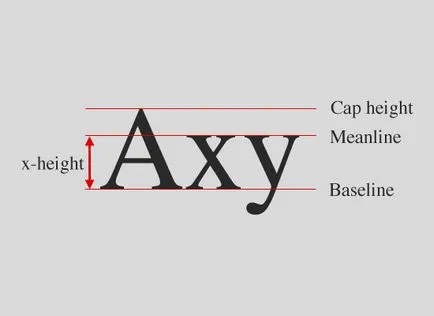
Headset ellen betűtípusok - mi a különbség?
Sokan használják a „Headset” és a „font” szinonimaként. Valójában ez nem ugyanaz a dolog, most fogom magyarázni, hogy miért.
Headset - stílusában hasonló sor karakterek írhatók / print. Ez a számok, betűk, szimbólumok. Betűtípus - szűkebb fogalom kotroe több tényező határozza meg, például méret, és a stílus. Általában Arial - ez a fejhallgató és Arial Bold - ezt a betűtípust.
besorolás
Betűtípusok több csoportra oszthatók - serif (talpas), sans serif (sans-serif), kézzel írott (script), aktsidentnye (kijelző). Vannak azonban más típusú osztályozás.
Serif betűtípusok, Antikva (Serif)
Az úgynevezett, mert minden betű van egy kis bevágás. Ha a nyomtatás nagyobb szövegtörzsek web design nem ajánlott, mivel azok ismerik nehezen olvasható. Ezek a betűtípusok általában használt megnevezéseket.
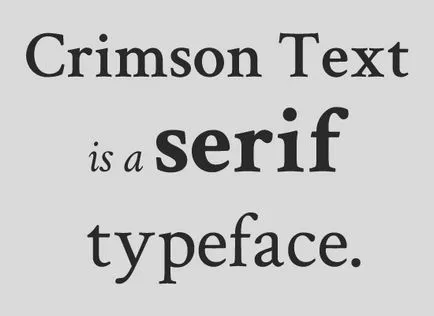
Mi serif betűtípusok helyett sok altípusok - például Old Style ( «Old Style” - ahogy nevezik Humanista, humanisztikus serif) - a legkorábbi betűtípus ezen osztályozás, használták őket annyira a távoli 1400-as. A megkülönböztető jellemzője - ez a része a szimbólum található, amely ferdén megcsináltak. Példák betűtípusok - Adobe Jenson, Centaur és Goudy Old Style.
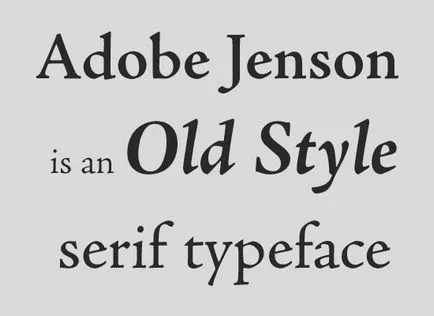
Átmeneti serifs (Átmeneti Serif) - használtunk a 1700-as években. Ez magában foglalja, mint a betűtípus Times New Roman és Baskerville, valamint Caslon, Georgia, és Bookman. Ezek a különbség vastag és vékony rész a betűk jobban észrevehető, mint a régi stílusú, de kevésbé feltűnő, mint a modern.
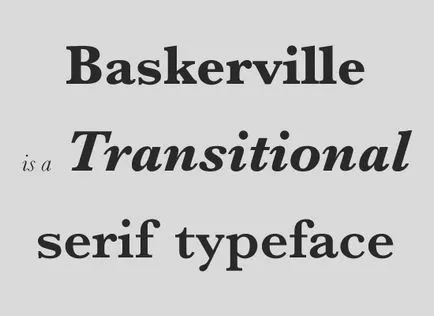
Modern serifs (Antiqua új stílus) - használt, miután a 1700-as években, és erős kontraszt a vastag és vékony rész a karaktereket. Ez magában foglalja a betűtípusok, mint a Didot és Bodoni
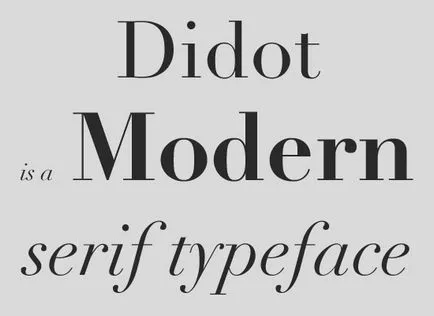
Végül Slab serifs (födém serif) - mind azonos vastagságú a vonalak, és a nagy serifs a végeken
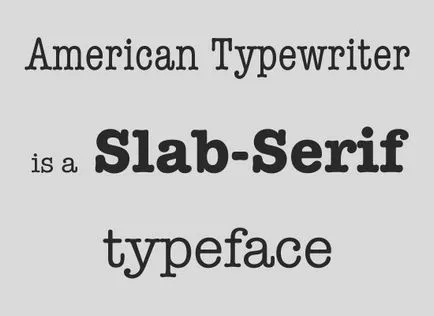
Talpatlan, groteszk (Sans Serif)
Apróra vágott betűtípusok így nevezték, mert nincs serif). Úgy néznek ki, modernebb, különben is, ők elkezdték használni a 18. században.
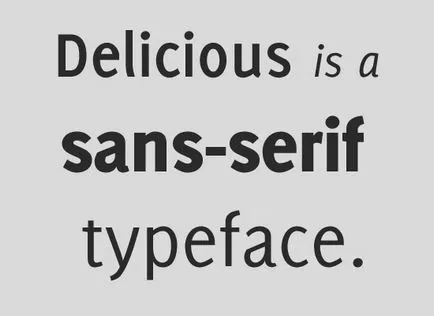
Itt van a 4 fő típusa vágott Font: Groteszk (Old groteszk), Neo-groteszk (új groteszk), Humanista (humanista) és a geometriai (geometrikus).
Régi grotesques - a legelső, úgy néznek ki, mint a serif betűtípusok, de nem serifs.
Például, Franklin gót és Akzidenze
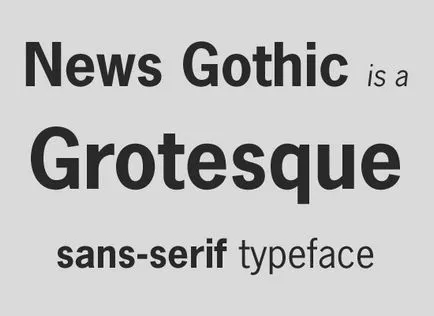
Új grotesques egyszerűsödnek, összehasonlítva a régi groteszk megjelenését. Túl sok mai legnépszerűbb betűtípusok új grotesques, például az MS Sans Serif, Arial, Helvetica és Univers.
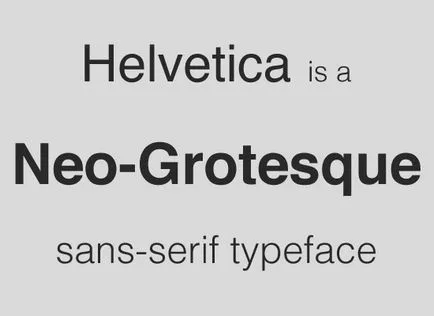
A humanisták - kalligrafichny több mint az összes többi talpatlan (azaz, hogy változik vonalvastagság). Ezek közé tartozik, például, a Gill Sans, Frutiger, Tahoma, Verdana, Optima, és LUCIDE Grande - gyakran használják a töltés a helyén a szervezetben.
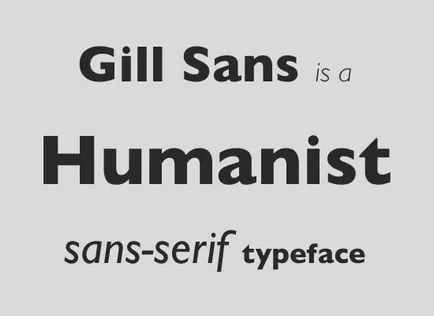
Geometriai alakzatok épülnek a jobb oldalon, például a „O” - egy kör, stb.; tekinthetőek a legkorszerűbb talpatlan. Példák - ITC Avant Garde Gothic, Erbar Groteskhez, Eurostile, Futura, Kabel, Metro, Neuzeit Groteskhez, Rodchenko, spártai.
Script (Script)
Script betűtípus alapja a kézírás. Kétféle betűtípusok - formális (hivatalos) és kezhl (alkalmi). Formai mintha kézzel írták, jönnek a 17-18 században. Néhány betűtípus alapulnak kézírás híres mesterek, mint George Snell és George Bickham. Példaként a modern betűtípus vehet Kuenstler Script. Szép és elegáns, ez nem alkalmas a főoldalon a szöveget.
Kezhl betűtípusok - egy modernebb változat, ez eredetileg a 20. században. Ez kevésbé formális, gyakran egy kövér stroke és a hatása ecsetvonásokkal. Ezek a betűkészletek Mistral és Brush Script.
Aktsidentnye betűtípusok (Display)
A nem-alfabetikus betűtípusok (Dingbats)
A nem-alfabetikus betűk - ezek betűtípusok, amelyek nem betűket, hanem tartalmazhatnak szimbólumokat és dísztárgyakat.
Arányos ellen monospaced
Az arányos font karakter veszi annyi helyet, amennyi szükséges a természetes írásban. Például Times New Roman betűtípus arányos. De szélességű betűtípusok, minden szimbólum az azonos szélességű. Ezek a betűtípusok közé tartozik például, Courier New
hangulat
font hangulat nagyon befolyásolja az a tény, hogy célszerű használni egy adott helyzetben. Elég gyakran használt kontrasztok - üzleti stílusban kombinálják az informális, fényes, drámai. Például Times New Roman - betűtípus szigorú, és hogy oly gyakran használt üzleti levelezés. Itt például, Helvetica még változik a hangulat, attól függően, hogy a környező betűtípusokat.
És színezőanyagok alkalmazott kimeneti eszközök is megvannak a maga sajátosságai. Biztonságos színpaletta maradt emlékezni.
Serif betűtípus könnyebben olvasható nyomtatott nagy tömb a szöveg. Nem csoda, hogy a jó könyveket díszített serif! Mivel ők nem azért, mert az adott képernyő (serifs rosszul látható) a képernyőn megjelenő betűtípusok.